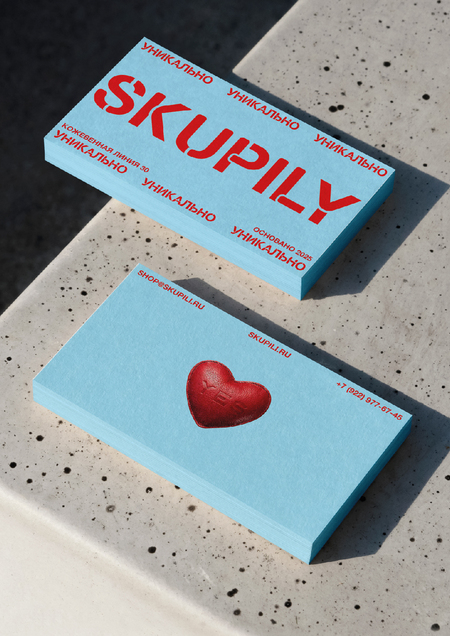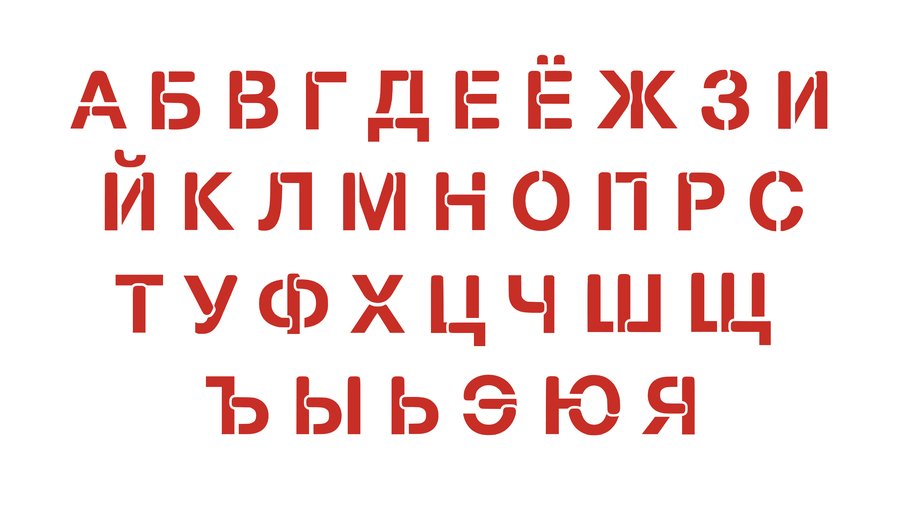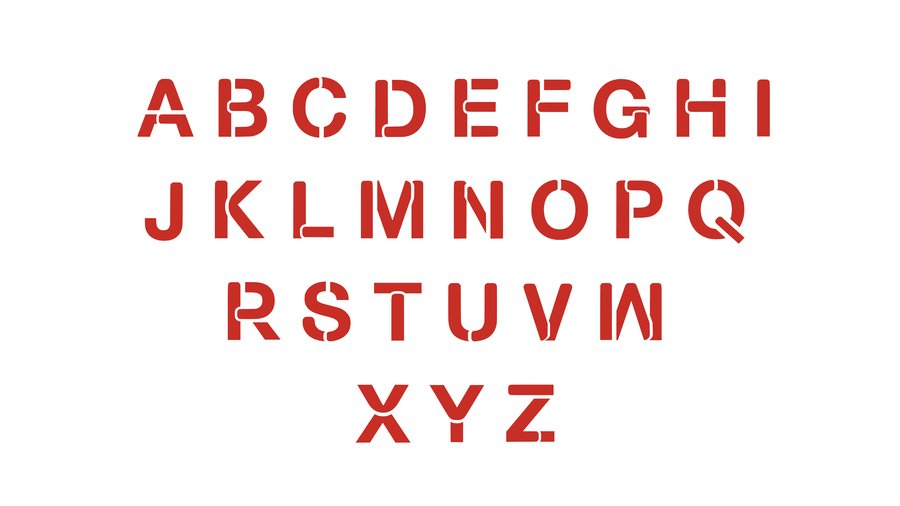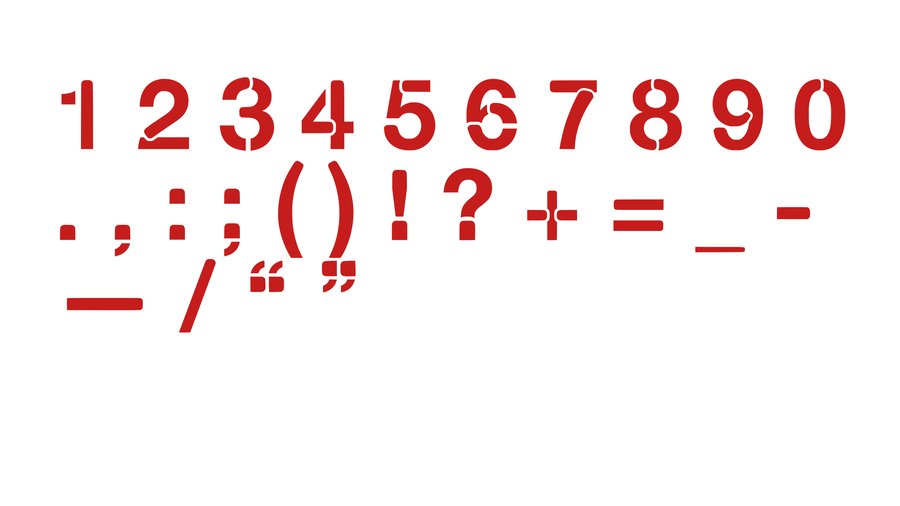
DUAL FONT
DUAL FONT — Это модульный шрифт, построенный на контрасте строгих прямых углов и мягких скруглений. Скругления расположены в верхней части элементов шрифта или на их средних элементах. В последнем случае выпуклость такого элемента формирует компенсирующую вогнутую выемку в прилегающем к нему перпендикулярном штрихе. Шрифт основан на Helvetica Neue Bold.